La tipografia e’ essenzialmente una forma d’arte alle volte non capita e spesso trascurata dai web designer. Alcuni talenti si sono messi in luce solo per la tipografia. In questo articolo vi presento alcuni lavori tipografici di spessore reperibili in rete. Alcuni di questi lavori sono di una semplicita’ disarmante, mentre altri sono curati e dettagliati, quasi delle opere d’arte. Comunque tutti questi lavori mostrano talento e abilita’. Mi auguro che troviate ispirazione nel vederli e che vi appassionerete di piu’ alla tipografia del web. Partiamo:
Neny
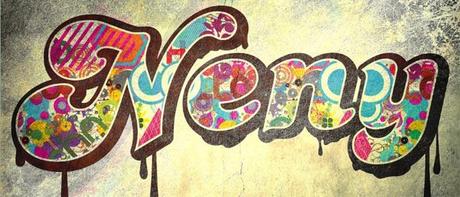
Gettin Loose
Danger
Street Art
Theme Park
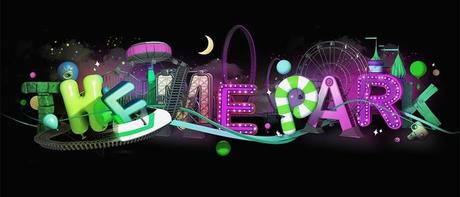
Awesome
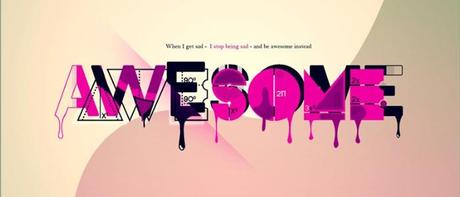
Work Play